マルチマスターフォント(MMフォント)はAdobe SystemsのType 1 PostScript フォントの拡張版であるが、 OpenTypeの登場と、特にOpenType 1.8でのOpenTypeフォントバリエーション(可変フォントとも呼ばれる)の導入により現在は廃止されている。[1] [2]
マルチマスター フォントには 2 つ以上の「マスター」(つまり、元のフォント スタイル) が含まれており、ユーザーはこれらのマスターを連続した「軸」の範囲に沿って補間できます。適切なアプリケーション サポートがあれば、これらの軸は必要に応じて調整できます。
その意図は、複数のマスターフォントを使用することで、デザイナーが文字グリフの完全性や可読性を損なうことなく、希望する正確な幅、太さ、光学サイズのスタイルを生成できるようにすることでした。その効果はモーフィングに似ており、デザイナーは2つのスタイルの中間を選択できます。たとえば、ボールドとレギュラーのスタイルを妥協してセミボールドフォントを生成したり、トレンドを拡張してウルトラライトまたはウルトラボールドを作成したりできます。このアイデアは新しいものではなく、URW++などの企業によって使用されていましたが、Adobeはテクノロジーをさらに発展させたいと考えていました。
Adobe のマルチマスターフォント技術の目標は、フォントのエンドユーザーが太さや幅などのパラメータを調整することで、状況に応じて必要なフォントを正確に作成できるようにすることでした。[3] [4] [5]しかし、マルチマスターフォントは、消費者向けデスクトップパブリッシングアプリケーションでサポートされるように作成(または書き直す)するのが難しいことと、フォントデザイナーが一般的に特定の太さとスタイルで、個別に微調整されたフォントファイルとしてフォントをリリースすることを好んだため、消費者向けの用途では人気がありませんでした。しかし、マルチマスターの概念はフォントデザインスタジオで今でも頻繁に使用されており、デザイナーはさまざまな太さとスタイルをすばやく生成し、個別に最適化することができます。 [6] [ 7]そのため、「マルチマスター」は、Adobe の技術を使用する必要はなく、一般的に補間フォントデザインを表す一般的な用語と見なされることがよくあります。[8] [9]
2016年、Adobe、Google、Apple、Microsoftは、 OpenType仕様の新しいアップデートを発表し、可変フォントを可能にしました。マルチマスターコンセプトと同様に、これにより、単一のフォントファイルからプログラム的にカスタムスタイルを生成できるようになります。[10] [2]
マルチマスターフォントの特徴
利用可能な場合、ほとんどの MM フォントは次の変数の 1 つまたは 2 つ (場合によっては 3 つ) をサポートします。
- ウェイトを使用すると、文字の太さを、通常は細字から標準字、極太字まで変更できます。
- 幅を使用すると、文字の幅を拡張または圧縮できます。どのフォントもソフトウェアで圧縮または拡張できますが、マルチ マスター フォントを使用した結果の方が優れています。フォントを人工的に拡張すると、線の太さなど、すべての機能が拡張されます。つまり、垂直方向のストロークが水平方向のストロークに比べて比例して太くなり、不均一な外観になります。幅軸を持つマルチ マスター フォントは、適切に拡大縮小されるように設計されています。
- 光学サイズを使用すると、読者にどのくらいの大きさで表示されるかに基づいて文字の形状を変更できます。サイズが小さい場合、セリフなどの細かいディテールやステムなどの細い線は、通常、太くなります。また、「x ハイト」(小文字の「x」の高さ) もフォント全体の高さに対する割合が高く、文字がわずかに拡張される場合があります。これらの変更は、小さな文字を読みやすくするように設計されています。サイズが大きい場合、これらのディテールはより細かくなり、線はより繊細になります。光学サイズは、文字の実際のサイズとは無関係であることに注意してください。アプリケーションと表示環境に適した光学サイズを選択するのはユーザー次第です (たとえば、看板では、非常に大きなテキストでも小さな光学サイズを使用する必要があります)。
- 複数のマスター軸の中で最も使用頻度の低いスタイルでは、他のフォント プロパティを継続的に変更できます。その一例は、セリフ スタイルをウェッジ (三角形) からスラブ (長方形) に変更することです。
たとえば、Myriadマルチマスターフォントには、「太さ」と「幅」という 2 つの軸がありました。したがって、このフォントには、各文字の 4 つの個別の「マスターデザイン」 (ライト圧縮、ライト拡張、ボールド圧縮、ボールド拡張) が含まれていました。これらのエンドポイント間の太さまたは幅のフォントは、これらのマスターデザインの文字アウトライン間を補間することで作成できます。[11] [12]イタリック体を追加するには、さらに 4 つのマスターデザインが必要です。
もう 1 つの例はAdobe Jensonで、「ウェイト」軸と「光学サイズ」軸をサポートしています。このフォントは、光学サイズ軸を表すために、それぞれ 6、12、72 ポイントのタイプ用に設計された 3 つのマスターを使用します。これにより、12 ポイントの共通サイズを最適化できますが、ローマン用に 6 つのマスター デザイン、イタリック用にさらに 6 つのマスター デザインが必要になります。
アプリケーションサポート
これらのフォントに対する現在のアプリケーション サポートは、まったくサポートされていないわけではないにしても、まばらです。ただし、FontLabやFontForgeなどのフォント デザイン ツールでは、MM フォントを編集したり、必要に応じて他のフォント形式にエクスポートしたりできます。Windowsおよび「Classic」Mac OS (9 以下) で MM をサポートするには、 Adobe Type Manager (ATM) が必要です。
この技術が失敗した理由について、タミー・リッグスがアドビのために書いた回顧録では、「ユーザーは試したいフォントのバリエーションごとにインスタンスを生成することを余儀なくされ、その結果、MinioMM_578 BD 465 CN 11 OP のような難解な名前のフォント ファイルがハード ドライブに散らばることになった」と述べている。アドビの著名なフォント デザイナー、キャロル・トゥオンブリーは、 1999 年頃にフォント デザインを辞める決断をした理由の 1 つとして、この失敗したプロジェクトのフラストレーションを挙げており、アドビのクリストファー・スライは後に、アドビの主任書体デザイナーであるロバート・スリンバッハが1990 年代後半にマルチ マスター技術をアドビ ジェンソンに適用しようと奮闘して健康を害したのではないかと心配していたと語っている。[4] [13]
フリーソフトウェア
マルチマスターフォントのフリーソフトウェアサポートは、マルチマスターフォントから標準 PostScript フォントを生成するプログラム mminstance によって提供されます。これらのフォントは、標準 PostScript タイプ 1 フォントと互換性のある任意のアプリケーションで使用できます。
FreeTypeフォント レンダリングエンジンは、複数のマスター フォント (および GX フォント) のレンダリング サポートも提供します。
マルチマスターフォントの遺産
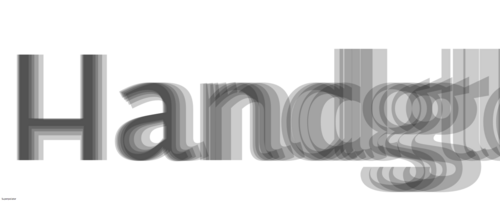
マルチプル マスター フォント形式は、主にOpenTypeに置き換えられました。OpenType は、さまざまな言語やグリフをより多くサポートしますが、文字の形状に対する独自の連続制御は提供しません。通常、古いマルチプル マスター フォントの OpenType バージョンには、最も一般的に使用される軸位置の組み合わせの選択が含まれています。
マルチマスターフォントには、依然として 2 つの目的があります。
- Adobe Acrobatのフォールバック フォント形式として、フォントが見つからない場合に元のフォントの代わりにマルチ マスター フォントが使用されます。Acrobat のデータ リソースには、Adobe Serif MMとAdobe Sans MMという 2 つの代替フォントが埋め込まれています。CourierStdは、 Acrobat の別のフォールバック フォント ファミリです。Foxit PhantomPDF などの他の PDF エディターも、この目的でマルチ マスター フォントを使用します。
- フォント ファミリを作成するためのデザイン ツールとして、フォント デザイナーは基本フォント デザインからマルチ マスター フォントを作成し、MM フォントの複数の軸からフォント バリエーションを構築して、顧客にさまざまなフォント バリエーションを提供できます。たとえば、フォント デザインのライト バージョンとヘビー バージョンを作成することで、ウェイト軸を持つマルチ マスター フォントを作成し、クライアントが希望するカスタム ウェイトを提供できます。Adobe やその他の企業は、フォント デザインでマルチ マスター テクノロジを引き続き使用しています。
現代のマルチマスターデザインでは、厳選されたウェイトのコレクションをユーザーに公開するのが標準であるため、どのサイズに補間するかが重要な問題となります。ルーカス・デ・グルートが開発したThesis書体では、デ・グルートが公開するウェイトの選択は「補間理論」を使用して開発されました。3つのステムa (最も細い)、b (補間)、c (最も太い) における光学補間b は、 aとcの幾何平均、つまりb ² = acに設定されています(線形算術平均とは対照的です)。[14] [15]